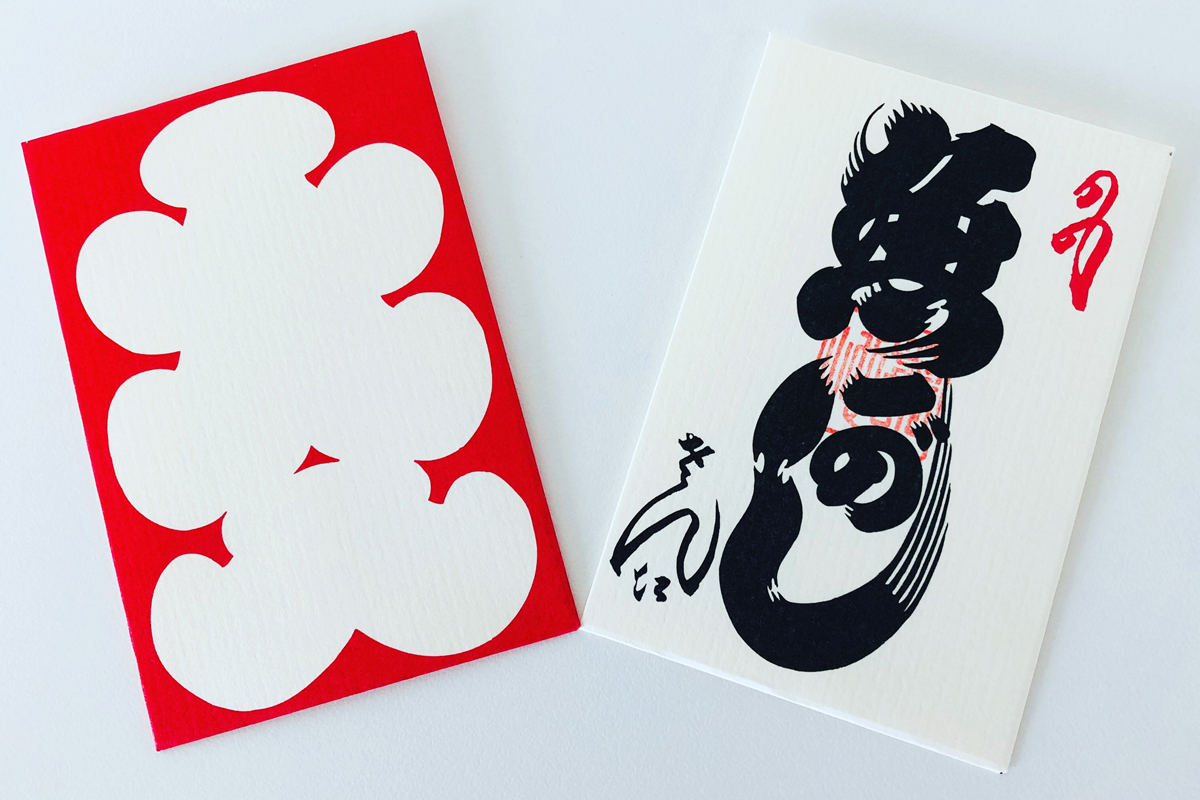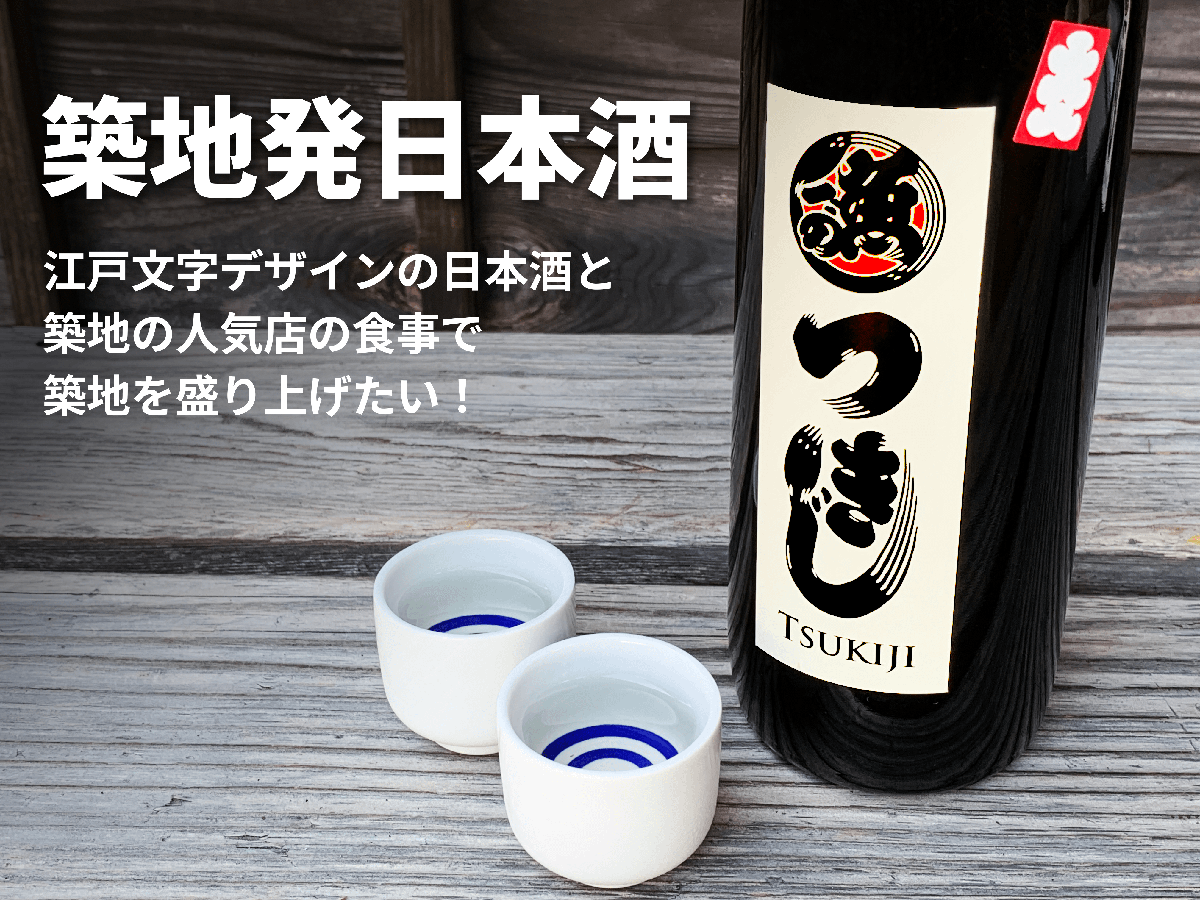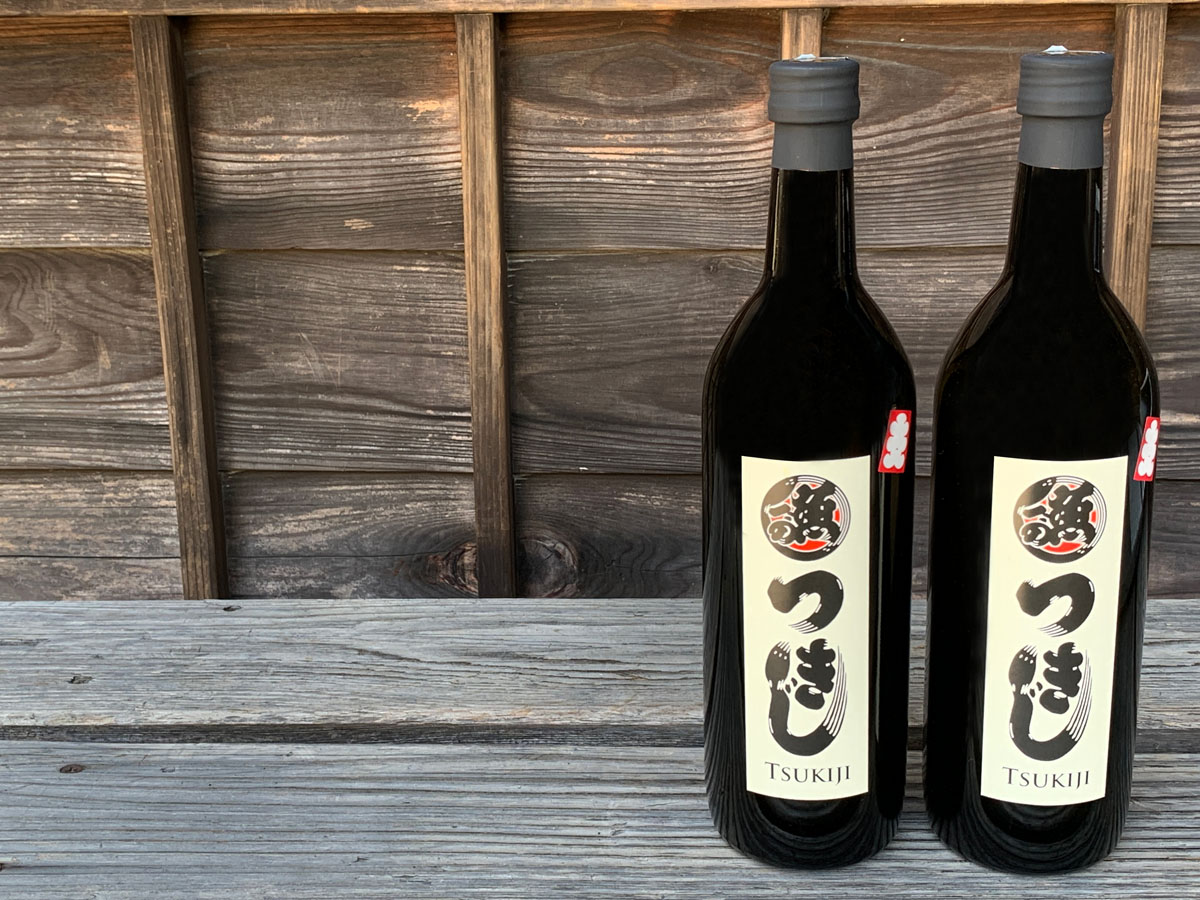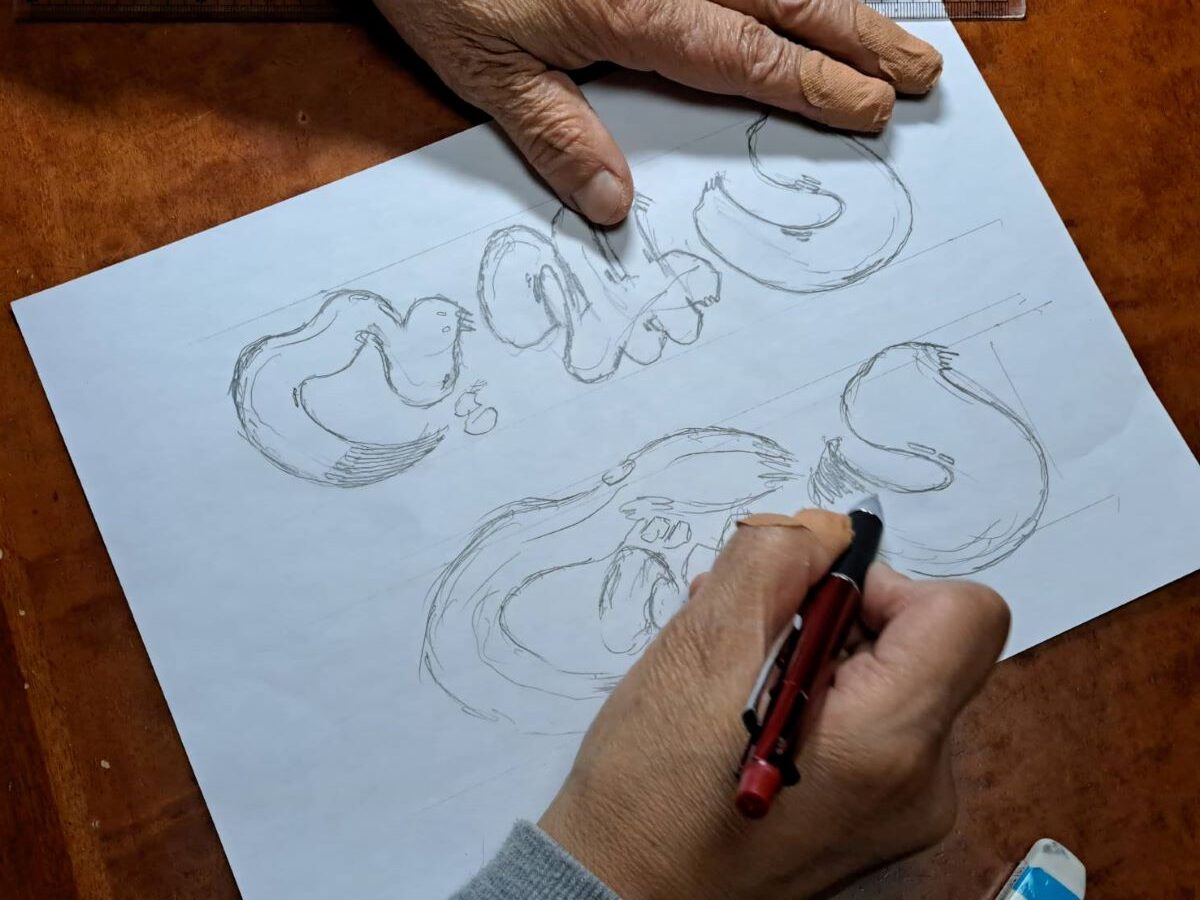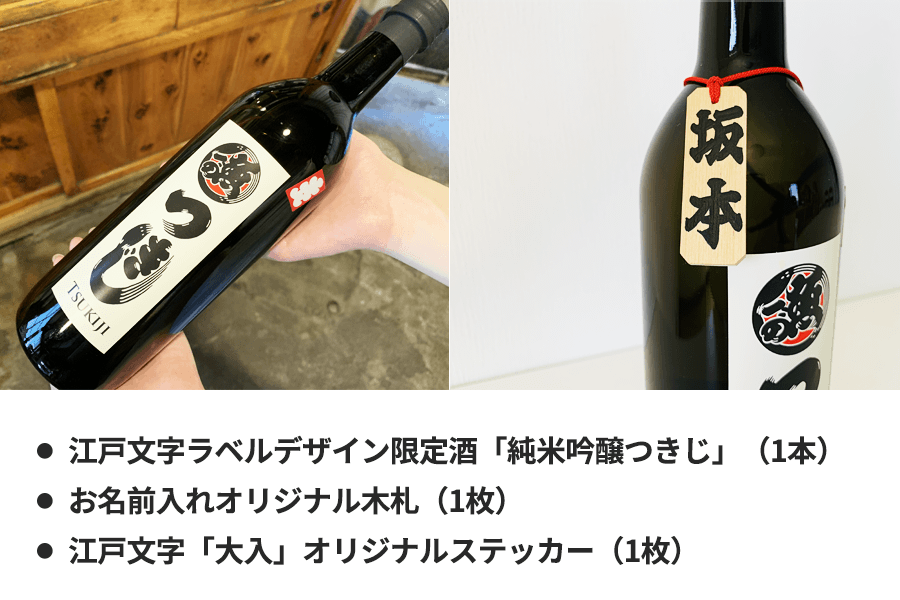
築地を応援するお酒が完成しました!
築地を応援する日本酒とは?
「築地市場の歴史を未来へと繋ぎ、多くの人々に築地の魅力を再認識してほしい。」そんな願いを込めて、企画された日本酒です。
江戸文字でデザインされた日本酒
築地発の日本酒の名称は、「純米吟醸 つきじ」です!
「純米吟醸 つきじ」の瓶を彩るのは、「江戸文字」で力強く書かれたオリジナルラベルです。
築地の地で、その伝統の技を守り、受け継ぐ江戸文字職人「津多屋商店」さんに書いてもらいました。
江戸文字の特徴は、文字と文字の隙間を少なく、太く書くことこれは「隙間なくお客様でいっぱいに」「商売が繫盛する」という願いが込められており、縁起が良いとされてきました。
江戸時代から続く日光の蔵元
築地と日光。
一見、遠く離れた二つの場所が、温かい絆で結ばれています。
蔵元の身内の方が築地に住まわれていて、江戸文字職人さんとの日々の親交を経て、今回のプロジェクトは始まりました。
天保13年(1842年)の創業より日光の地で歴史を刻む蔵元、「渡邊佐平商店さん(わたなべさへいしょうてん)」です。
栃木県日光市に位置する渡邊佐平商店さんは、豊かな自然に恵まれた環境で、代々受け継がれてきた伝統的な酒造りを守り続けています。
日光の社寺の一つとして世界遺産に登録されている「日光二荒山神社(にっこうふたらさんじんじゃ)」。
お酒の神様として有名な神社に、渡邊佐平商店さんの日本酒が奉納されています。
今回のプロジェクトでは、渡邊佐平商店さんが、築地発の日本酒の企画に応え、酒造りの全面的な協力を快諾してくださいました。
築地で大人気の飲食店
食の街として賑わい続ける築地の「今」を、そして「これから」を、さらに多くの方に感じて欲しいという強い想いがあります。
今回、その想いにご協力を頂いたお店が、創業54年の老舗蕎麦屋「長生庵さん(ちょうせいあん)」です。
食のプロである市場関係者や多くの食通に愛され続けてきたその実力は、まさしく本物。
蕎麦屋でありながら、築地ならではの新鮮な魚介を使った絶品料理や、こだわりの日本酒が楽しめるお店として、多くの人々を魅了しています。
長生庵さんとのご協力で、今回日光の蔵元さんの酒粕を使ったクラファン限定のお食事メニューをご提供頂くことになっています。
江戸文字の「津多屋商店」さん、日光の蔵元「渡邊佐平商店」さん、築地の蕎麦処「長生庵」さんからご協力を頂いております。
築地の歴史と文化、そして人々の温かい繋がりを次世代へとつなぐための架け橋として、日本酒「純米吟醸 つきじ」が誕生しました。